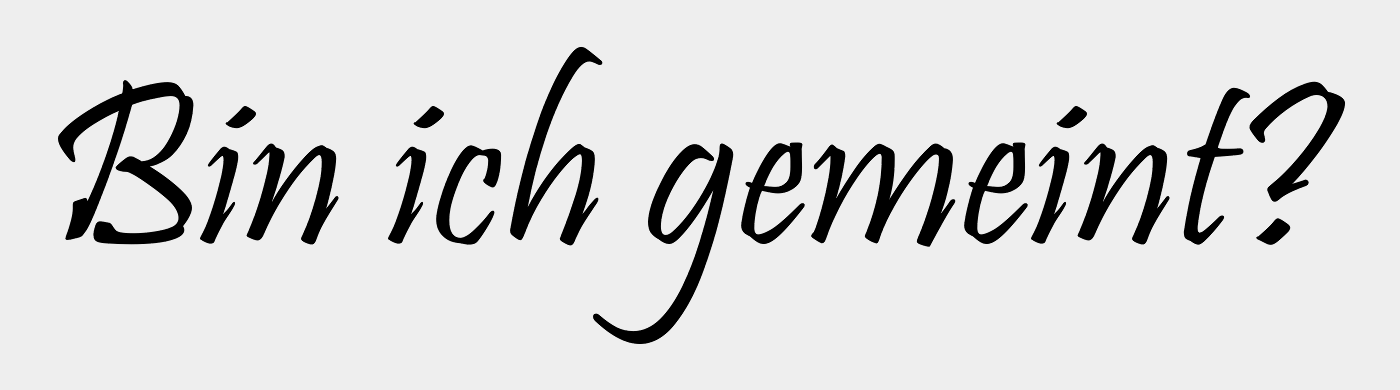
Pristina-Bold-Alternative?
HAllo, ich suche nach einer guten Alternative zu Pristina in BOLD. Ich möchte diese Schrift plotten, aber die originale Pristina, die ich habe wirkt zu dünn. Gibt es Pristina in bold oder eine Alternative dazu?
Spontan musste ich ja an Veljovic und seine Ex Ponto denken. Die ist zwar anders aber … schau selber:
Ansonsten würde ich bei den üblichen Verdächtigen für Handschriften mal gucken: Laura Worthington, Måns Grebäck oder Alejandro Paul bzw. Sudtipos :-?
Danke, aber diese Schrift kann ich nicht zum Beflocken nehmen. Sieht aus, als wenn die schon ausgefranst ist. Ich habe mich jetzt für die CascadeLightBT entschieden.
Warum nicht?
Keine glatten Ränder und ist auch ziemlich dünn. Diese Schrift geplottet und geflockt sieht halt aus als wenn sie schon anfängt sich aufzulösen. Zum Beflocken muss ich dicke und glatte Linien haben.